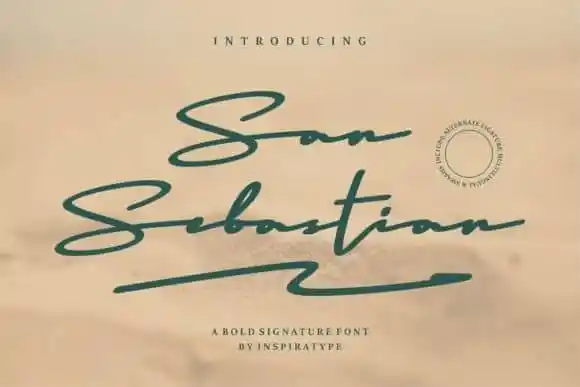
San Sebastian Handwritten Font – Download Grátis
San Sebastian Handwritten Font é uma elegante fonte de escrita cursiva que traz consigo aspectos divertidos e contornados. Originada no Inspiratype Studio por 99designs, esta tipografia atinge um equilíbrio perfeito entre a influência clássica da caligrafia e o sentimento contemporâneo e atual. Possui linhas monolineares com uma aparência rústica e jogadas de texto, que permitem criar escrita casual e pessoal. San Sebastian oferece um desenho limpo e moderno, adequado para projetos digitais em qualquer plataforma, aprimorando o visual do seu design. Seja você designer ou criativo digital, esta fonte é perfeita para aqueles que buscam uma abordagem fresca e divertida à escrita cursiva. Adotá-la em seus próximos trabalhos vai lhe permitir chegar aos níveis mais altos!